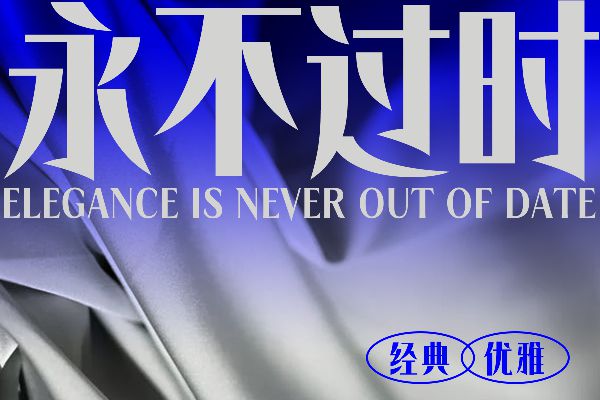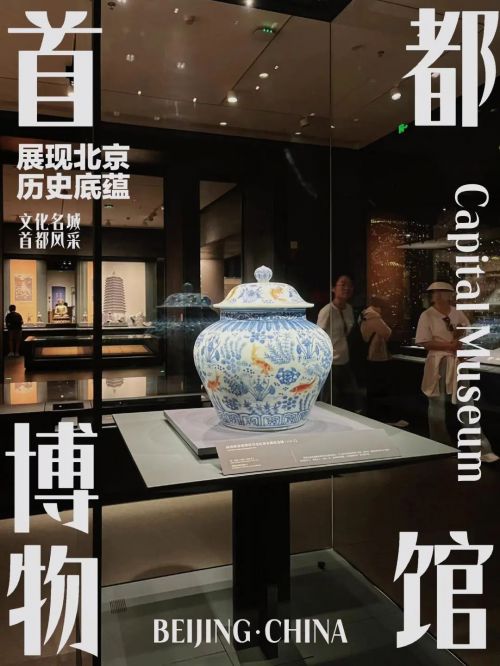
Aa锐雅体
Aa锐雅体是Aa字库推出的一款简体中文创意字体,以尖锐风格为核心设计语言,兼具女性气质与现代美学,是品牌视觉升级的优质选择。 Aa锐雅体字形修长,重心偏高的设计赋予字体轻盈向上的视觉张力,中宫宽博则让整体布局疏朗通透,既保证了设计的独特性,又兼顾了阅读的舒适感。笔型上,字体以利落直角为基础,搭配巧妙斜切与精致装饰元素,其中尖锐的下垂笔画尤为亮眼——如锋芒般的线条既保留力量感,又通过细腻弧度传递女性气质;笔画粗细均匀,方头设计强化了现代工业风,断开的连接方式则为字体注入节奏感,让每个字符都成为独立的设计单元。 作为一款粗体创意字体,Aa锐雅体将“简洁优雅”融入细节,适用于品牌LOGO、包装设计、广告文案等多元场景。目前,Aa锐雅体授权范围为企业专享/单独授权/品牌字体,助力品牌打造专属且富有记忆点的视觉符号。